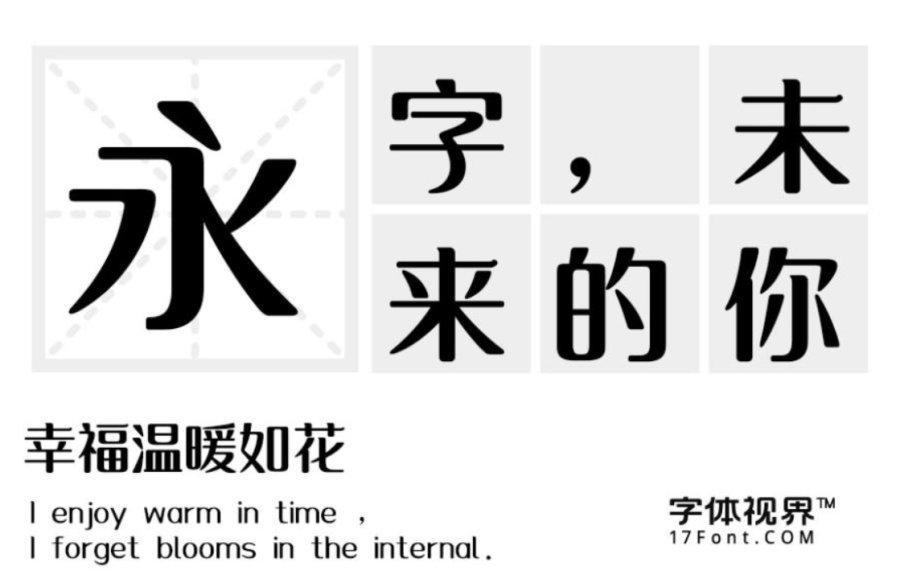
上首水滴体|一款艺术创意感十足的字体
上首水滴体发布
字体名称:上首水滴体
字体类别: 创意字体
适用场景:标题、正文、印刷、屏显、动漫、影视、广告
上首水滴体简介:上首水滴体,字体转角圆润,笔端圆滑似水滴,疏密有致,稳重不失俏皮。适用于搭配标志、广告标语、商业广告等高端属性。
上首水滴体预览图展示: